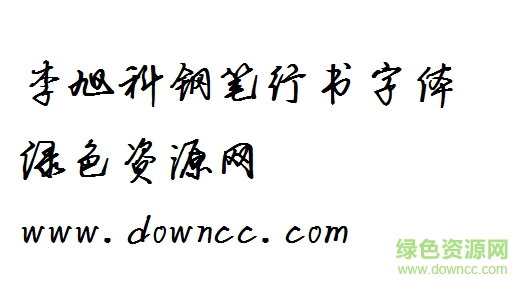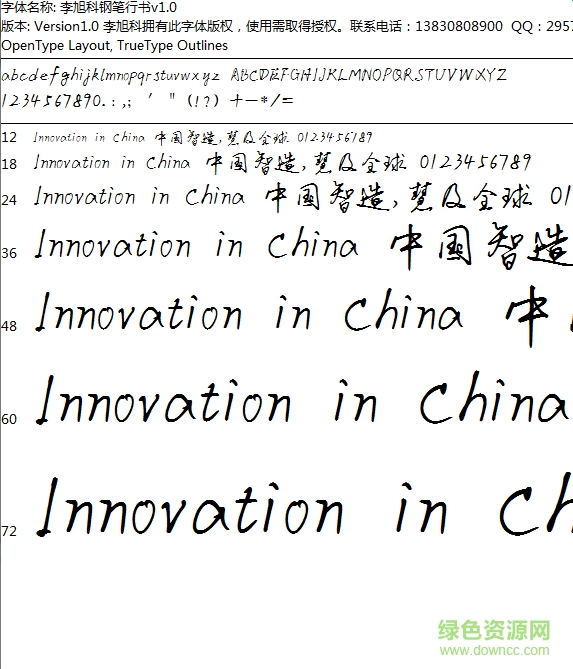
李旭科鋼筆行書字體是一款李旭科書法家系列行書字體,鋼筆行書盡顯細膩唯美,筆畫放浪不羈,整體效果十分好看,更多類似字體下載盡在綠色資源網!
李旭科鋼筆行書字體是一款書法家字體,該字體筆畫細膩,尾部的甩尾有力且有豐富的筆觸細節(jié),大字效果突出且引人注目;并且最大程度還原作者書寫字形,細節(jié)表現(xiàn)完整,且字庫完整,可以廣泛應用于名片設計、新聞媒體、宣傳海報、ppt、影視制作以及內容用字等領域。
該字體屬于非常優(yōu)雅的行書行列,字體筆畫隨意,非常的文雅脫俗,整體效果十分時尚好看,感興趣的朋友歡迎免費下載使用!